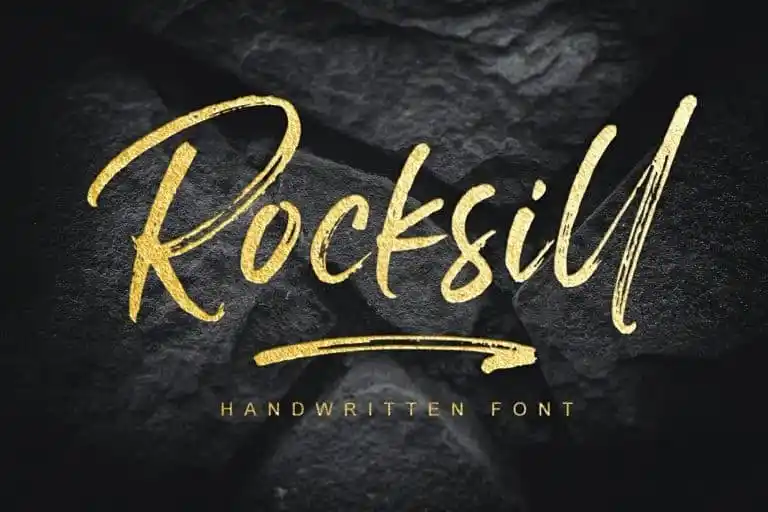
Rocksill Brush Font – Download Grátis
A ‘Rocksill Brush Font’ é uma mão-dura tipografia feita à mão, com um estilo texturado e natural. Desenhada por alphArtype, essa fonte traz a sensação única de arte livre para projetos criativos como marcos d’água na fotografia, capas de álbum, logotipos, cartões de visita e muitos outros trabalhos de design. Seja você um designer gráfico ou apenas alguém que ama criar, ‘Rocksill Brush Font’ é uma escolha perfeita para aqueles momentos em que sua paleta de fontes está prestes a esgotar. Com seu estilo fluido e vibrante, essa fonte natural pode transformar o modo como você expressa suas ideias. Não hesite em explorá-la para trazer um toque único aos seus projetos.